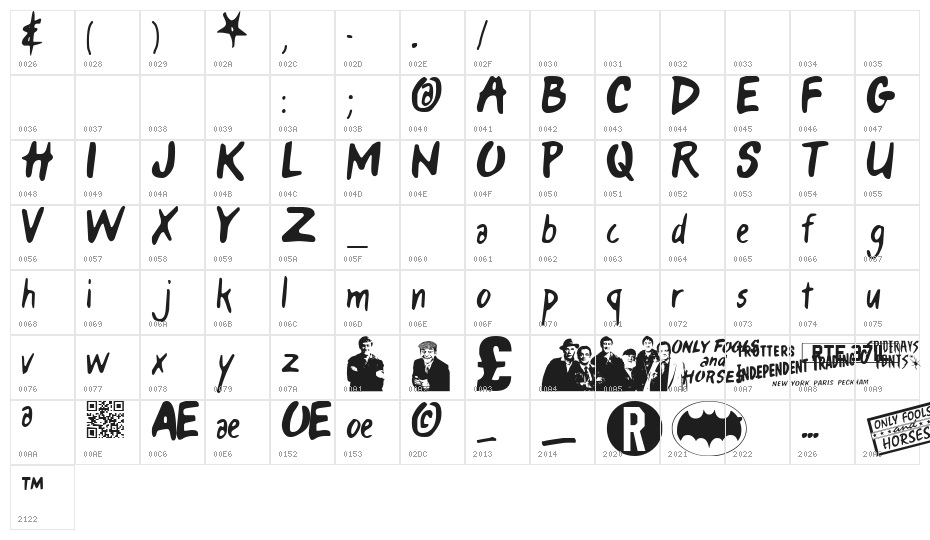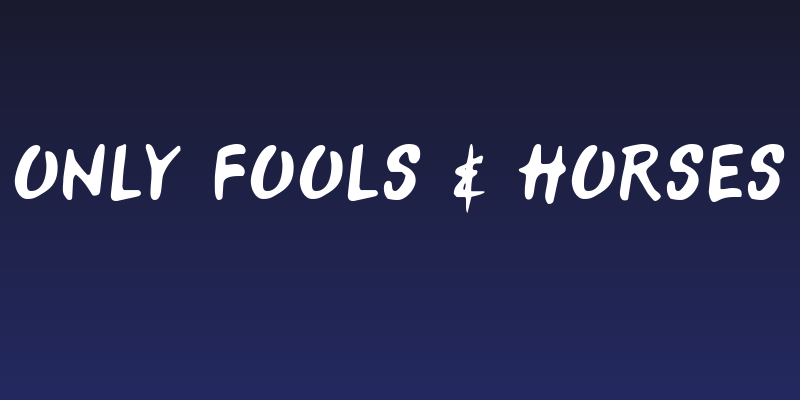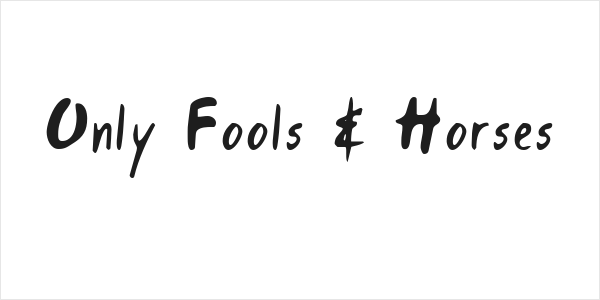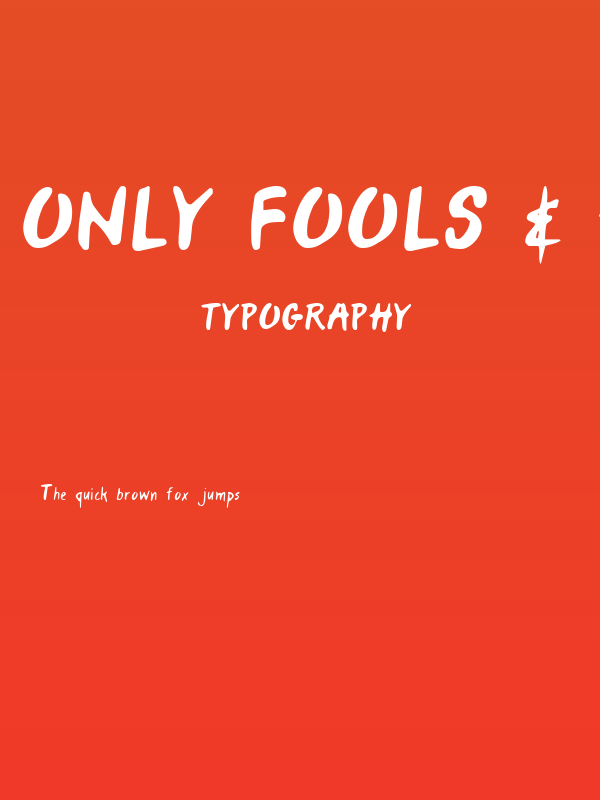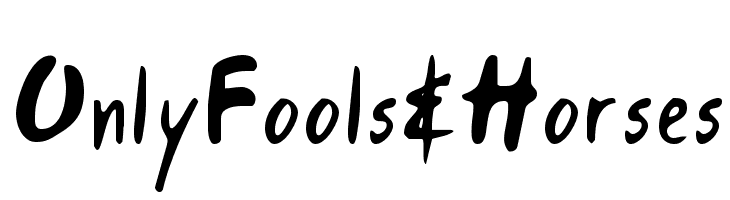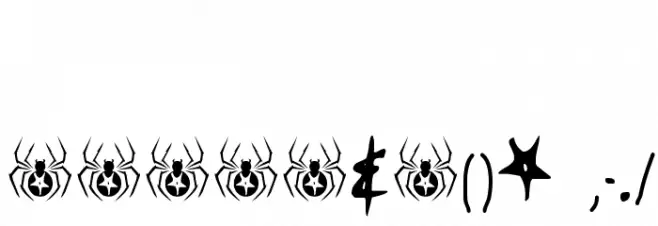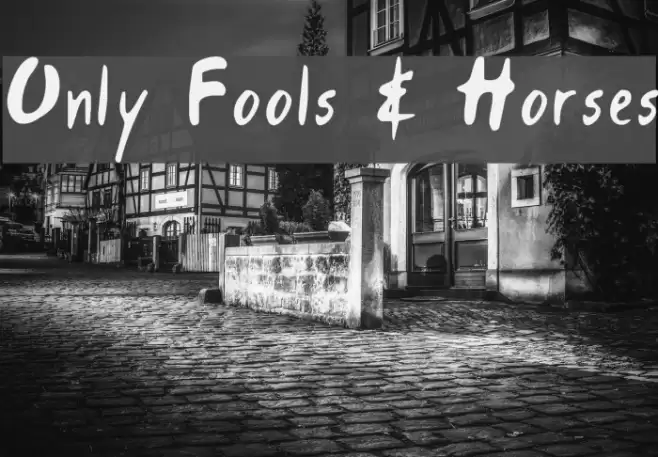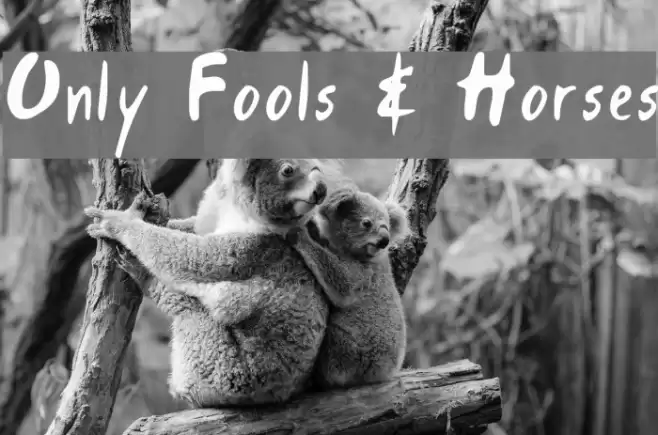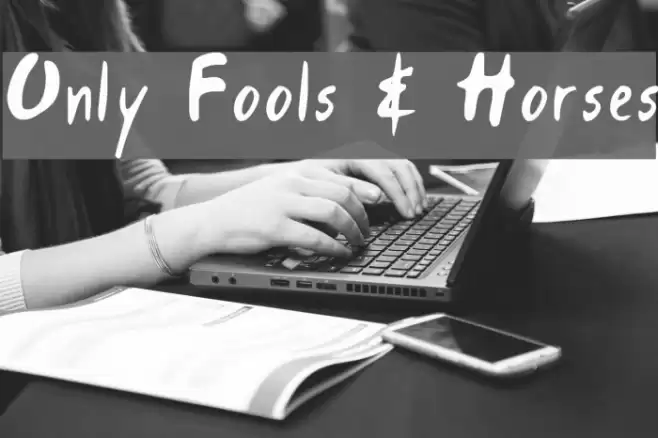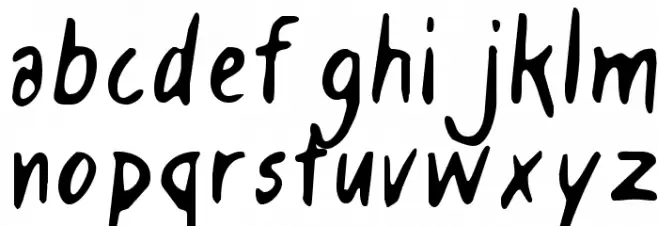
Only Fools & Horses Font
✎ TV show
| Catégories | TV show |
| Style général | Playful |
| Cas d'utilisation | Headlines, Logos, Informal Text |
| Projets proposés | Ideal for children's books, playful branding, informal invitations, and creative projects. |